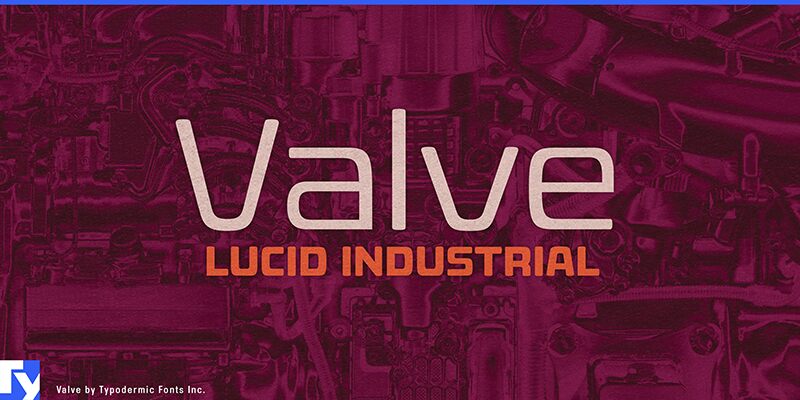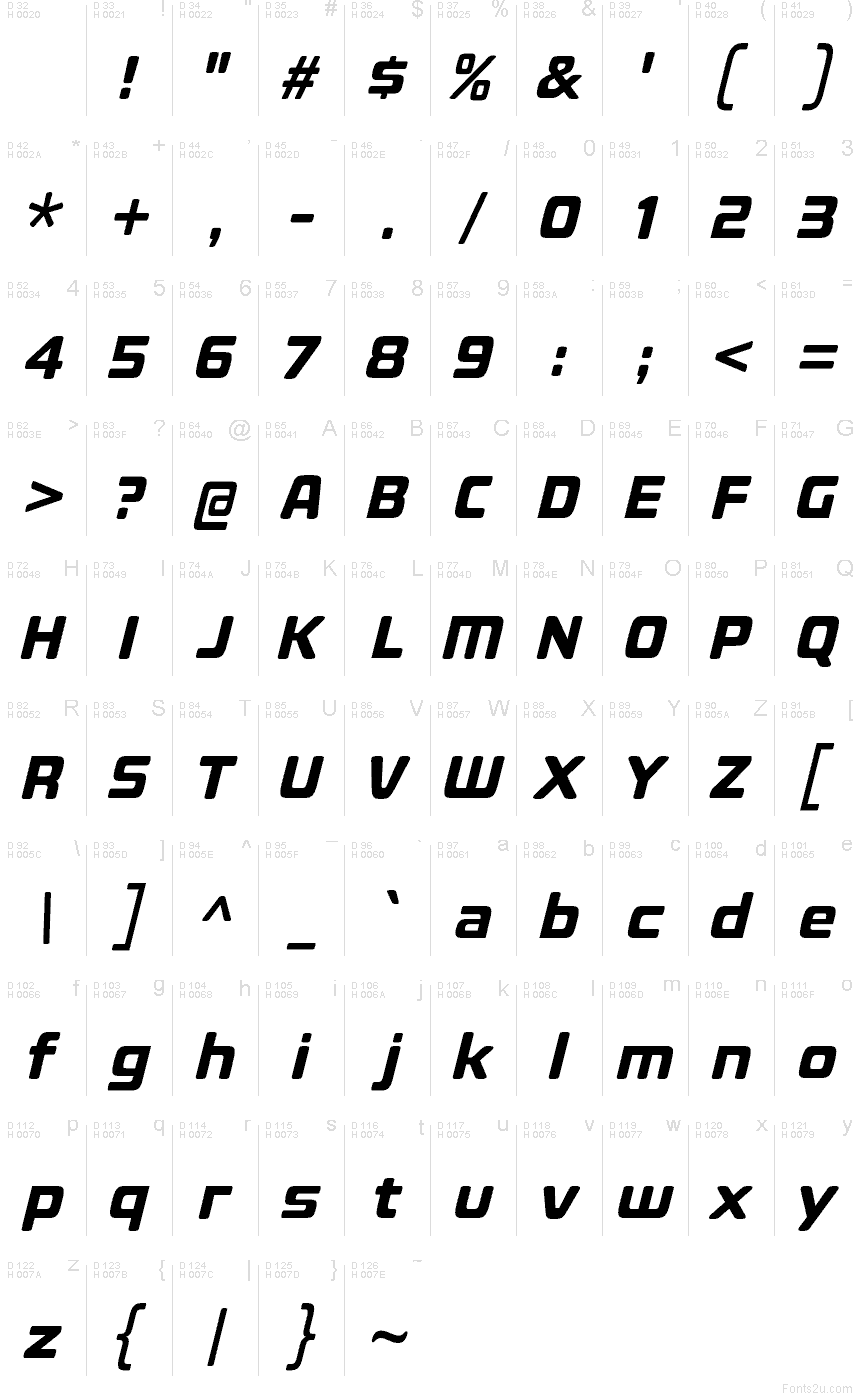
Valve Bold Italic od Typodermic Fonts to bezpłatny, pogrubiony, kursywny krój techno display, który oddaje aerodynamiczną energię wczesnego brandingu cyfrowego. Mocne pochylenie, złagodzone narożniki oraz szerokie, ciasno dopasowane znaki tworzą dynamiczny, spójny wygląd, unikając przy tym sztywnej mechaniczności.
Ten bezpłatny krój idealnie pasuje do grafiki wyścigowej, logotypów gier, brandingu oprogramowania, okładek albumów czy opakowań sportowych o futurystycznym charakterze. Sprawdza się również w krótkich nagłówkach i tytułach, gdzie ciężkie kształty oraz bliskie odstępy pozwalają uzyskać zwarty, ciągły napis.
Valve posiada zrównoważone proporcje oraz szerokie wsparcie dla języków łacińskich.